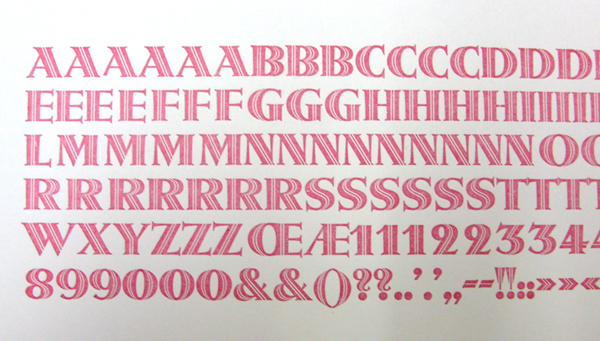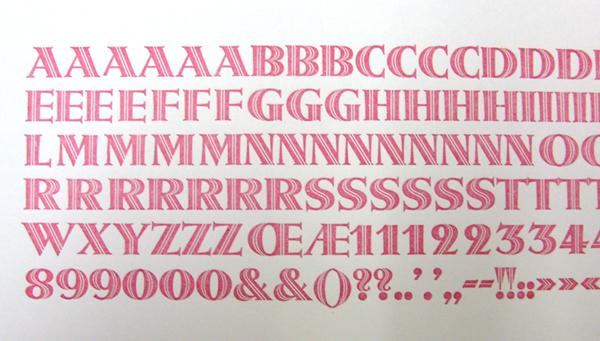
Antiqua-Variante (Bleisatz), aber wie heißt sie?
Anhängend das Bild der gesuchten Schrift. Ich würde gerne den richtigen Namen auf den Steckschriftkasten schreiben.
das könnte die lichte (oder offene oder schraffierte oder irgendwie so ähnlich genannte) Metropolis sein (von der es auch einen Schnitt ohne Verzierung gibt)  ... hab aber gerade meine Schriftmuster nicht zur Hand zwecks genauer Kontrolle ... also nur unter Vorbehalt aus dem Kopf ...
Aber "shaded" hieß der Schnitt im Bleisatz mit Sicherheit nicht ... wenn ich mich richtig entsinne ist das ne Bertholdschrift gewesen oder zumindest auf alle Fälle aus ner deutschen Gießerei und da hieß so etwas anders ...
Dieser Hinweis nur wegens der stilsicheren Beschriftung am Kasten ...
Genau, Metropolis licht, Willy Schwerdtner 1928, D. Stempel AG. Das konnte ich jetzt im Schriftenverzeichnis von Hans Reichardt nachlesen. Ich habe mir zwar auch vor meiner Frage schon sein Verzeichnis durchgesehen, aber irgendwann ist man wohl betriebsblind.
Aber "shaded" hieß der Schnitt im Bleisatz mit Sicherheit nicht ...
Ich kann mir vorstellen, dass der Schnitt im nicht-deutschsprachigen Raum "shaded" genannt worden sein könnte. Ist aber nur eine Vermutung.
Diese Vermutung stimmt sogar - die Amis zumindest haben diesen Schnitt (nach Import) "shaded" genannt. Aber welcher europäischer Bleisetzer beschriftet seine Kästen mit amerikanischen Bezeichnungen für deutsche Schriften?
»Metropolis licht« sagt Global Type.
Aber welcher europäischer Bleisetzer beschriftet seine Kästen mit amerikanischen Bezeichnungen für deutsche Schriften?
Ich kann nur konstruieren: Wenn das Blei vom Erbonkel aus dem fernen Amerika stammt … oder fkd gar nicht in Europa sitzt ;-) Think global.
Die amerikanischen Verwandten hatten leider nichts zu vererben und wenn dem so gewesen wäre, hätte ich dann nicht mit der Schrifthöhe ein Problem? Haben die nicht  62,03 Punkt?